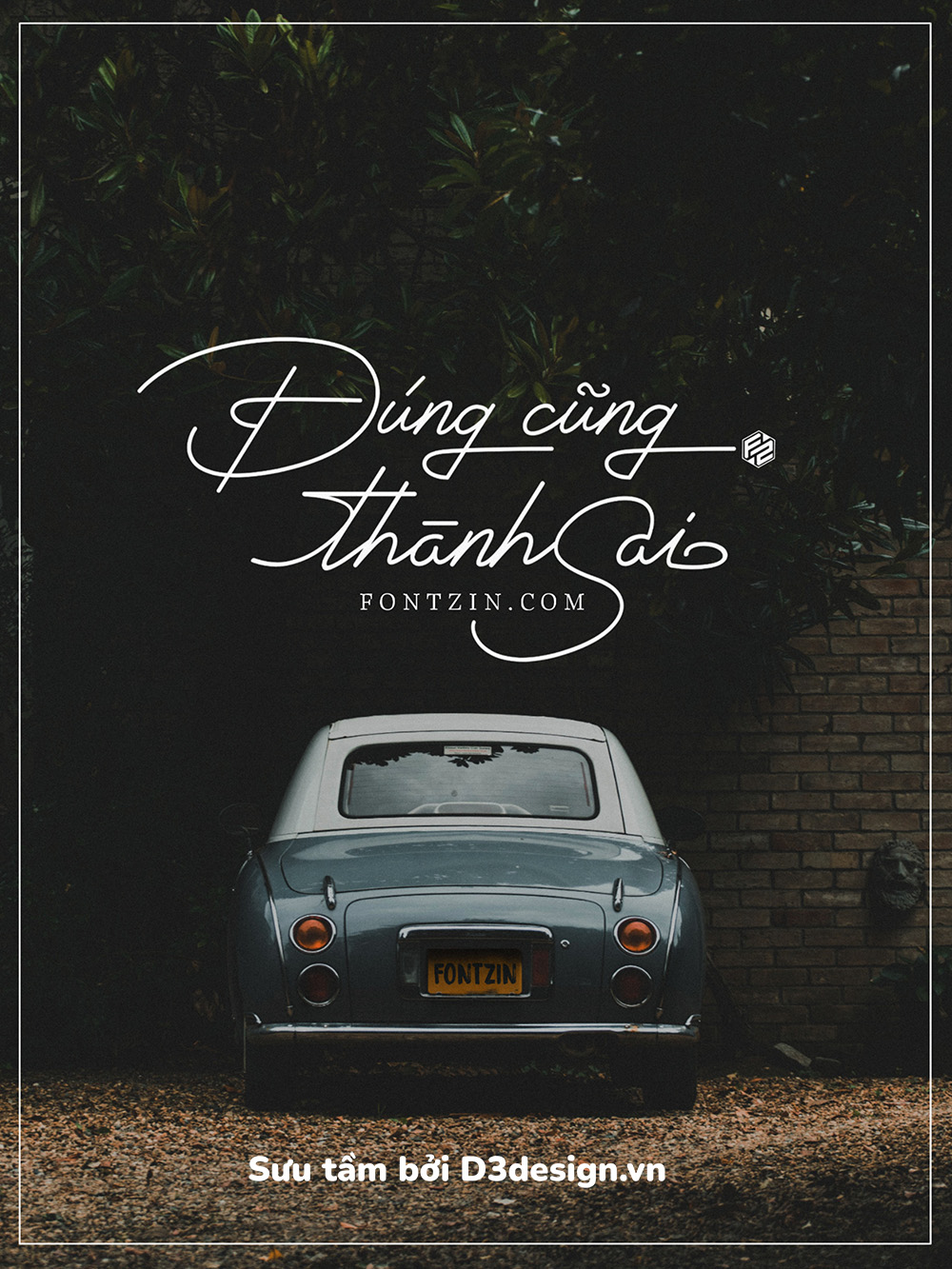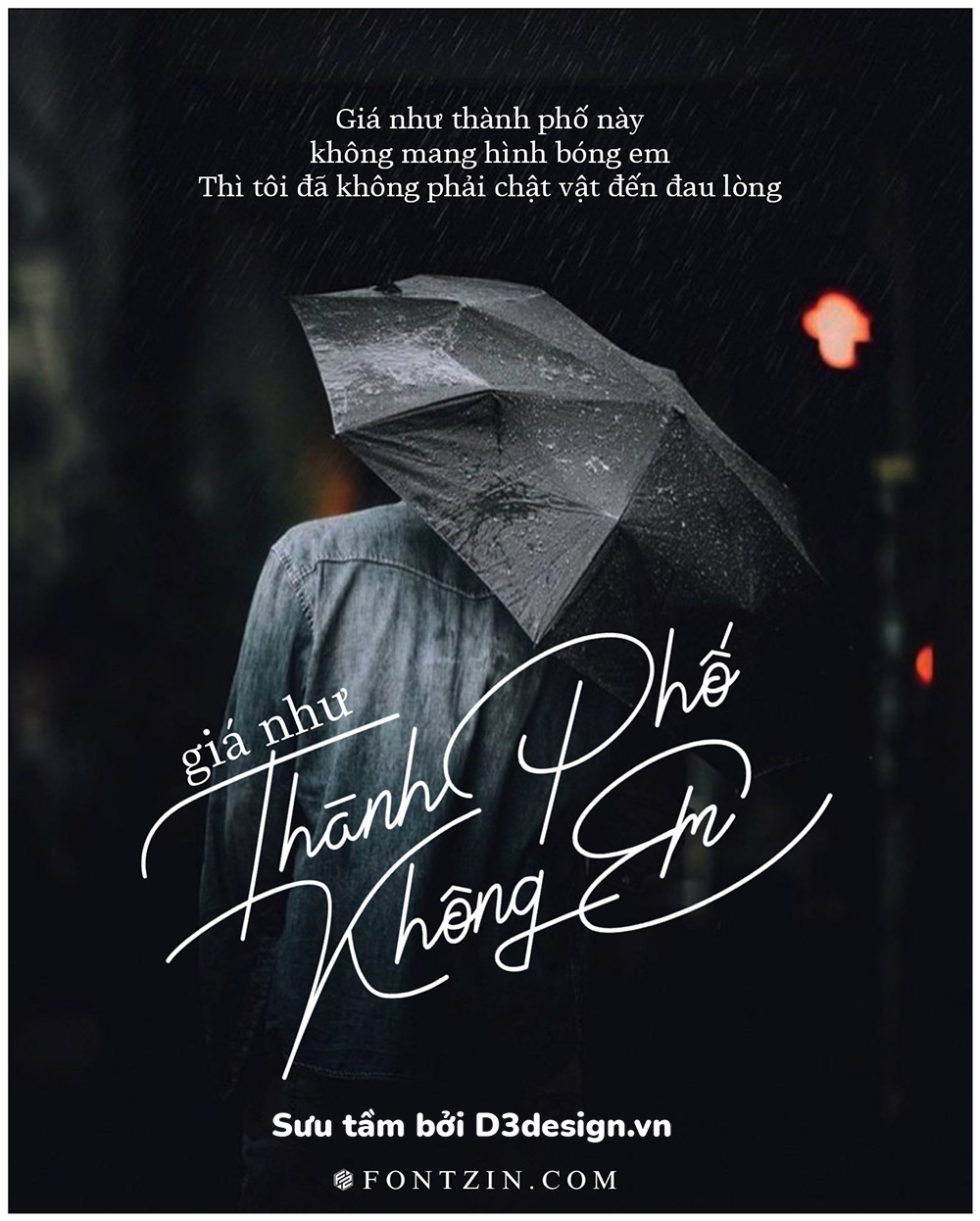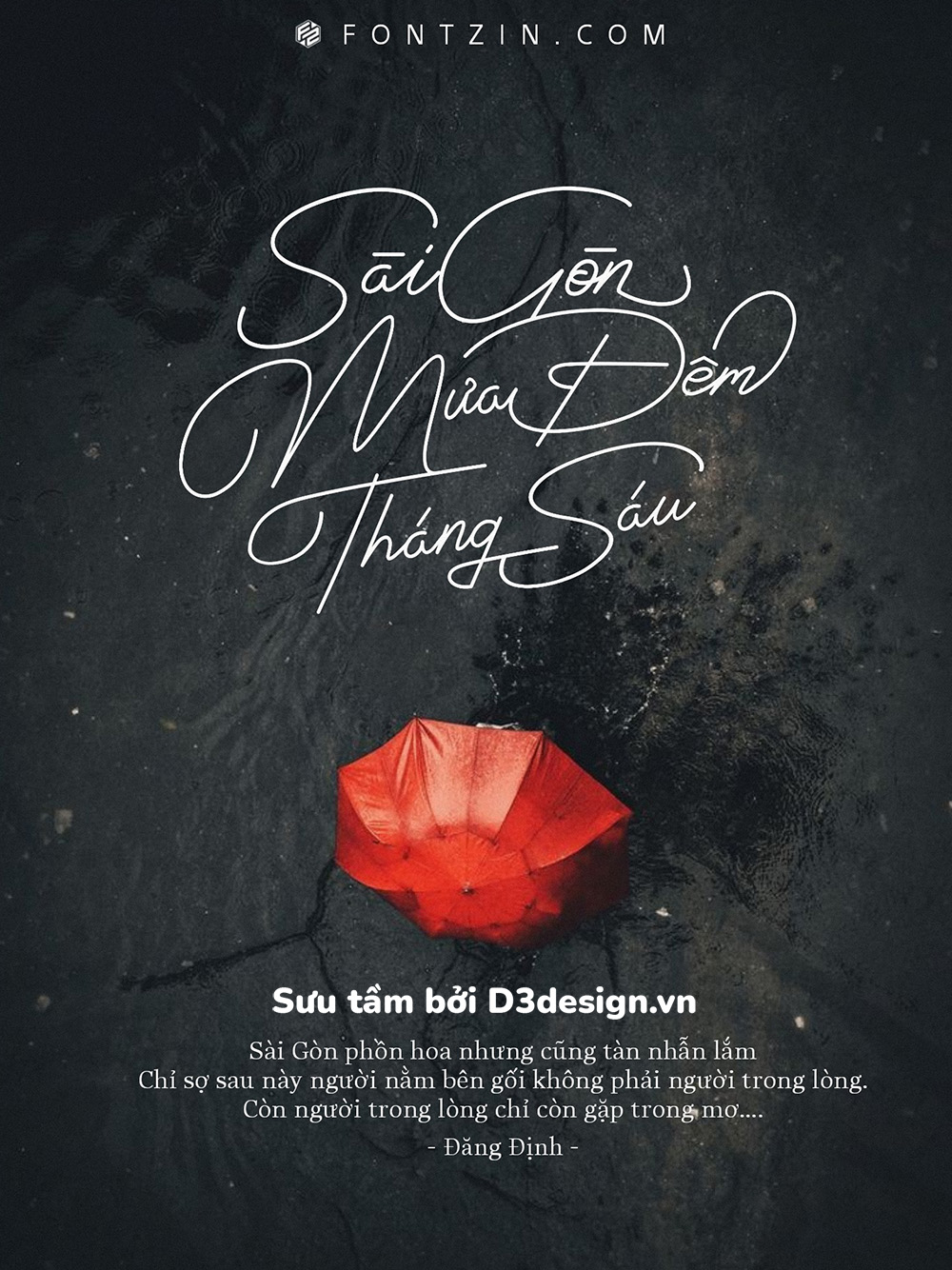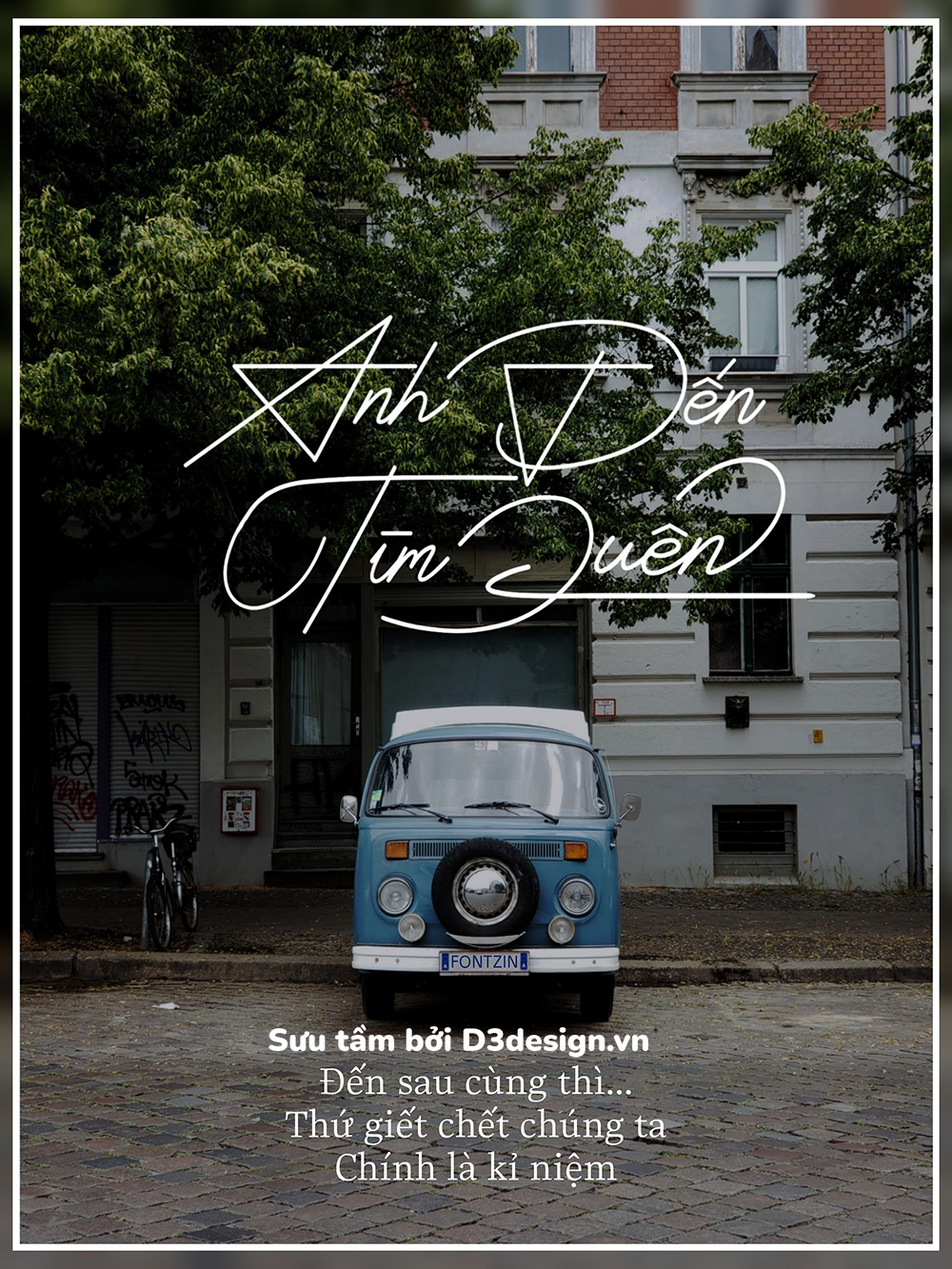
Font Việt Hóa - Presidente Font Chữ Ký Việt Hóa Cực Đẹp
Font chữ ký Signatory được thiết kế bởi Typeline. Font được thiết kế dựa trên nét chữ của tác giả.
Font mang phong cách hiện đại kiểu dáng kết hợp chữ ký và script vậy font vừa có sự độc đáo, cá tính của chữ viết tay vừa có sự mềm mại liền mạch của script.
Font chữ ký việt hóa theo phong cách của fontzin bởi Thái Hiếu (bạn nào cần việt hóa font ib trực tiếp anh ấy nhé).